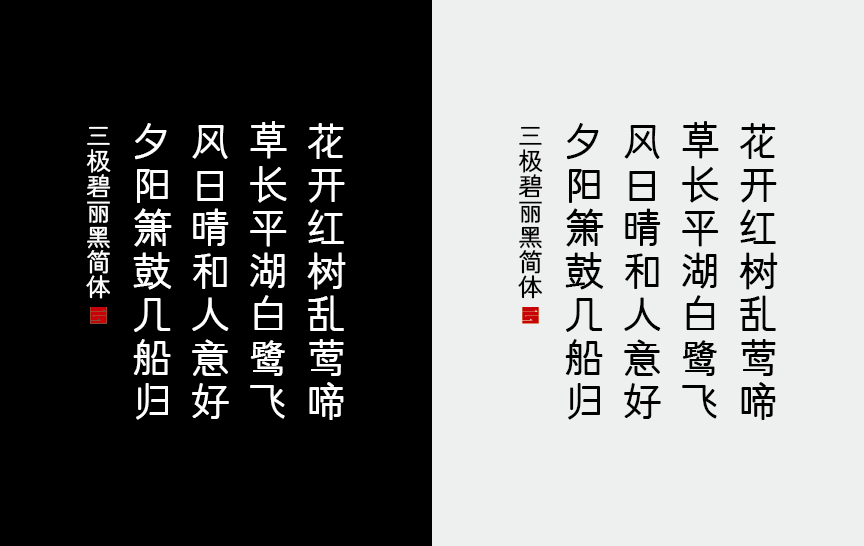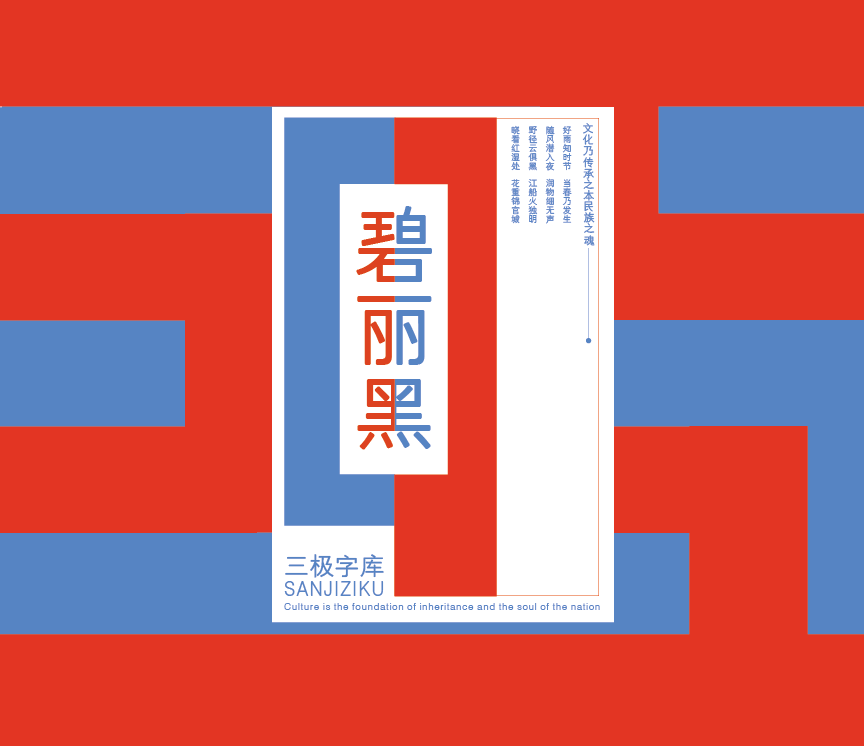
三极罗丽黑简体-粗
字体名称:三极罗丽黑简体-粗
设计师:罗碧霞,庞丽珊
所属分类:黑体
三极罗丽黑简体字形风格舒展柔和,起笔收笔皆为圆,折笔刚柔并济细节饱满,撇捺圆润柔美而又简洁明快,整体时尚而又不失端庄优雅。本款字形适用于品牌标志、招牌、包装、广告、游戏、设计等众多场景应用。
适用媒介:报纸、杂志、书籍、广告、标志、宣传册、空间导视、包装、影视、屏幕显示、交互设计。